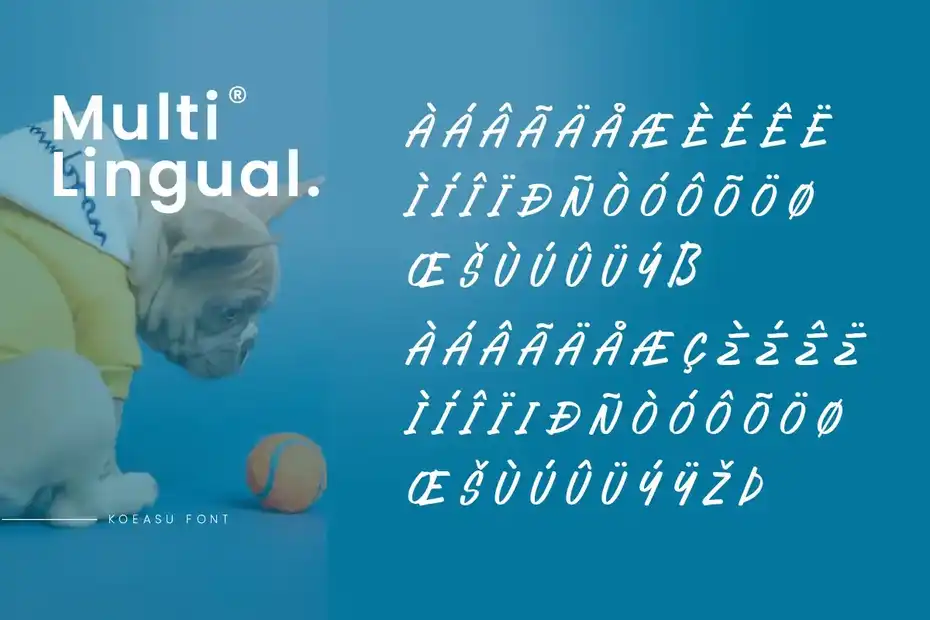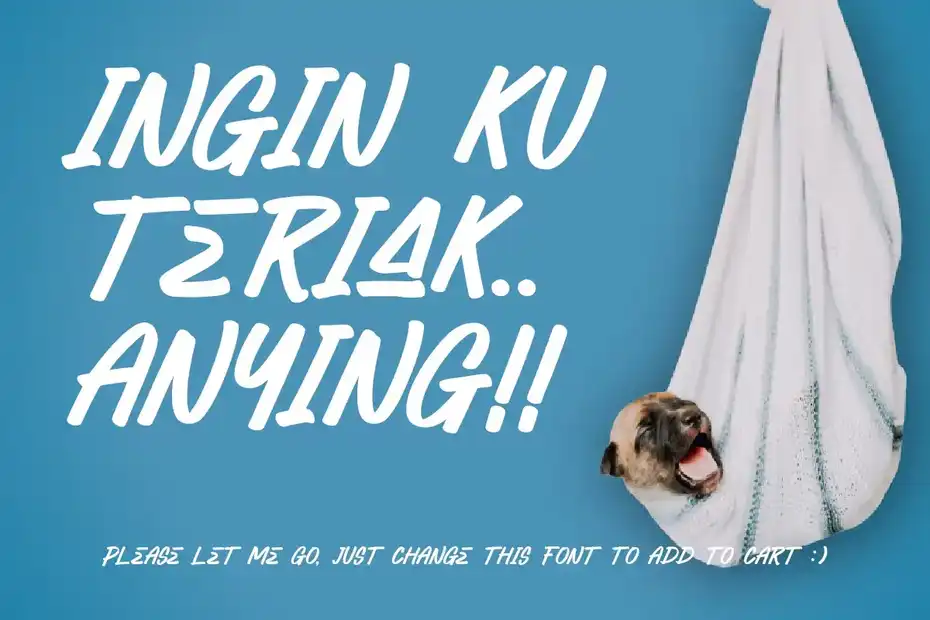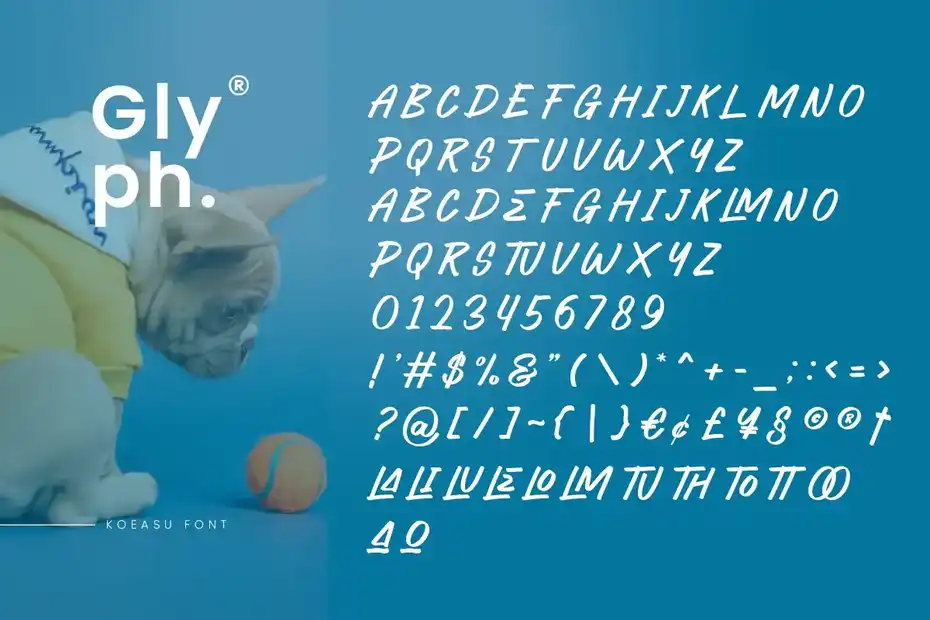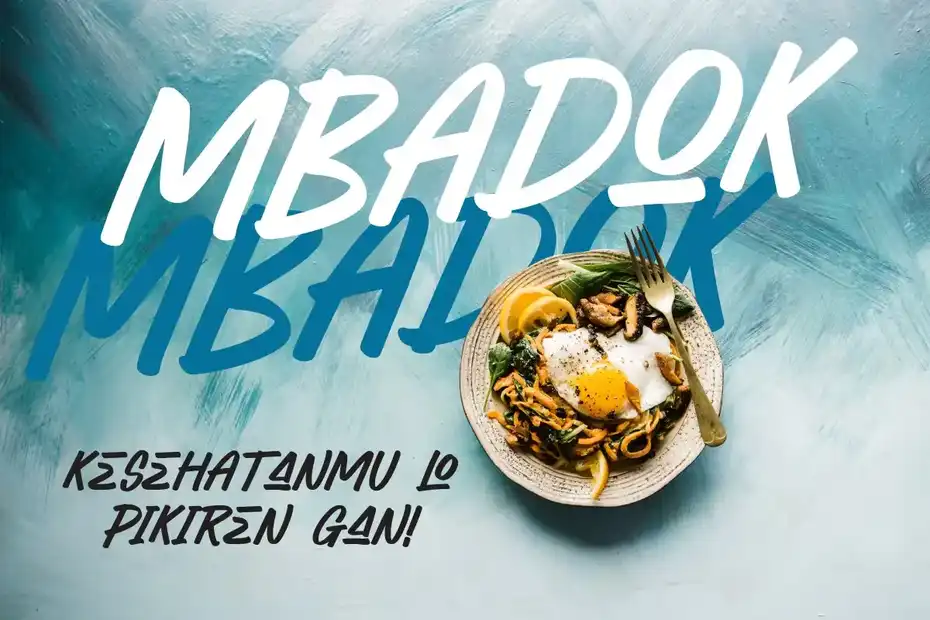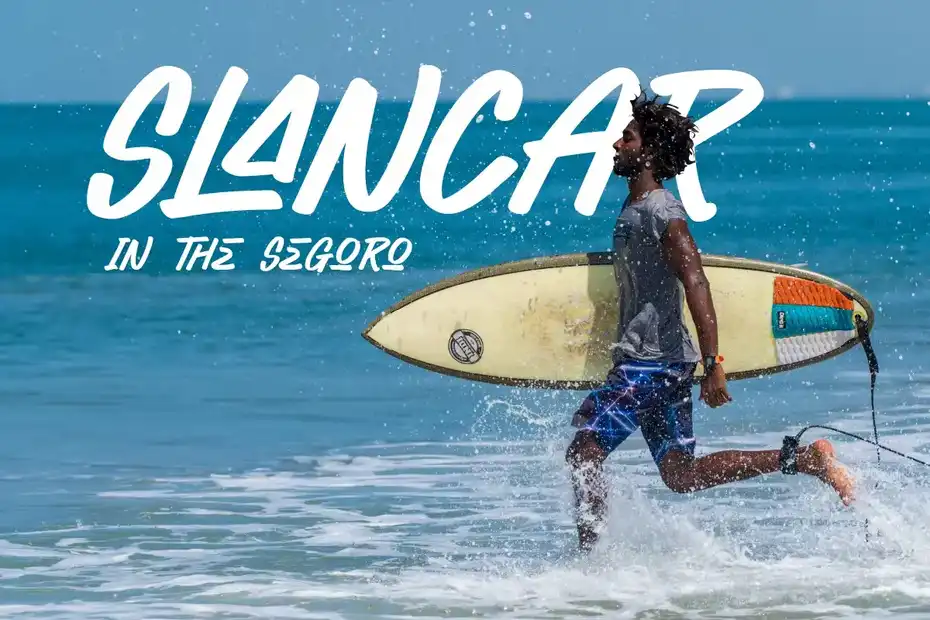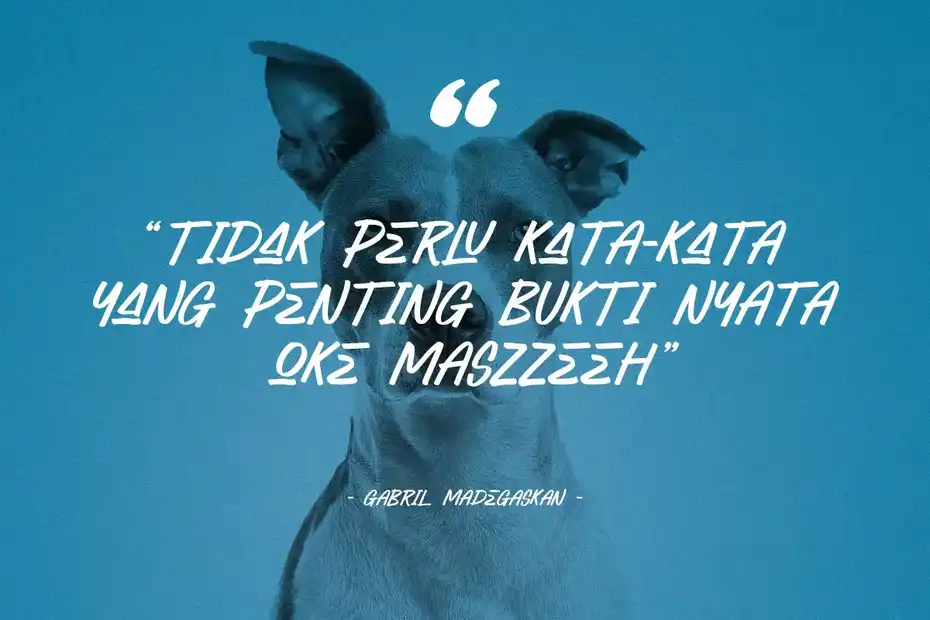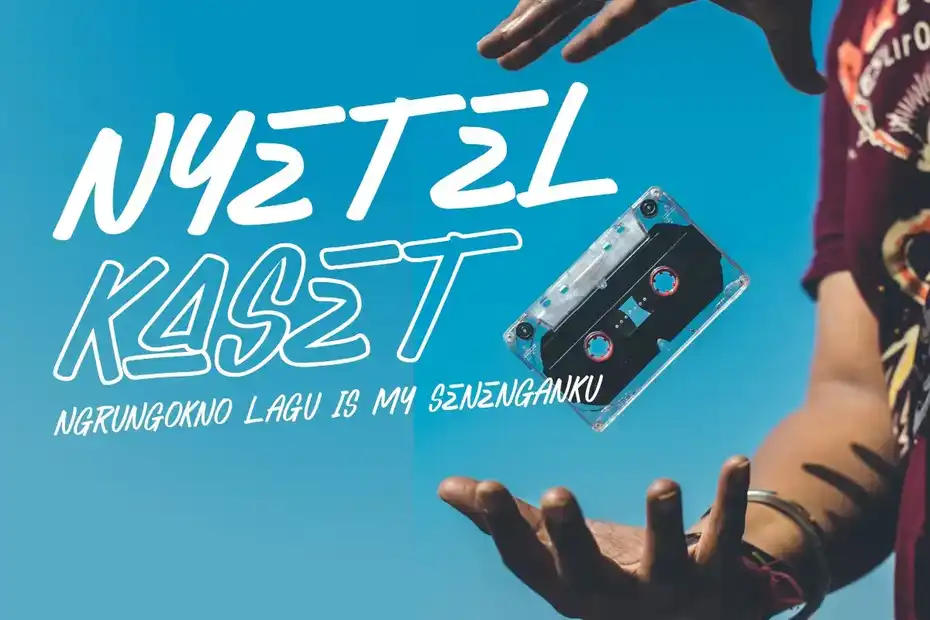
دانلود فونت انگلیسی KOEASU – Misuh Display Font
فونت انگلیسی KOEASU – Misuh Display Font : این مجموعه شامل یک فونت دست نویس است که برای لوگو، نقل قول، محصولات، تیشرت ها، بسته بندی، کمیک ها، مجلات، پوستر ها، رویداد ها، پست شبکه های اجتماعی، کتاب ها و پوشش متنی بر روی تصویر پس زمینه مناسب میباشد.